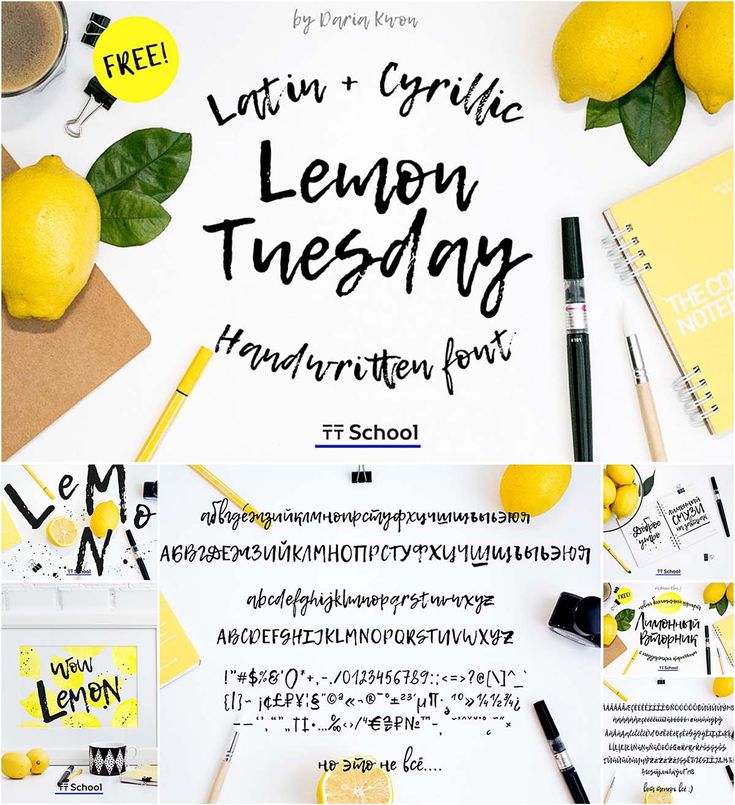
Бесплатный рукописный шрифт Lemon Tuesday — кириллица
В данном посте я хочу познакомить вас с отличным примером рукописного кириллического шрифта, выполненного на основе каллиграфии. Это Lemon Tuesday от Daria Know и Ivan Gladkikh. Шрифт распространяется авторами бесплатно для личных и коммерческих целей по лицензии OFL. Давайте разберемся, когда он будет уместен и где его можно скачать.
Шрифт Lemon Tuesday создан на основе написанных от руки символов. Он содержит не только кириллическое, но и латинское начертания. А так же набор цифр и специальных символов. Буквы выглядят немного потертыми, как-будто повторяя текстуру крафтовой бумаги или неровной штукатурки.
Такой рукописный шрифт подойдет для:
- логотипов
- оформления презентаций, пригласительных билетов
- дизайна афиш и постеров
- акцентных заголовков в веб-дизайне или полиграфии.
Лучше всего Lemon Tuesday будет сочетаться с изображениями и фотографиями природной тематики, гранжевых текстур и рисунков, выполненных сухими кистями.
Шрифт настолько самостоятелен и интересен, что его можно использовать как главный элемент креативной типографики, например, в интерьерных картинах.
Пример использования шрифта Lemon Tuesday в дизайне интерьерной картины
Рукописный шрифт Lemon Tuesday реалистично смотрится в виде надписей и заголовков на бумаге.
Это демонстрирует следующий мокап.
Надпись «от руки» шрифтом Lemon Tuesday
TypeType Foundry here to present you the new free super accidental font, Lemon Tuesday Handwritten Font. This typeface is based on expressive author calligraphy by Daria Kwon.
This font had emerged during the online course “Your Font” by Typetypeschool in August 2016. Lemon Tuesday is first of all that suitable for short emotional inscriptions. Therefore it will be great for creation of beautiful content in social networks and specialized media. Moreover, the font includes a standard set of Cyrillic characters and an extended Latin set.